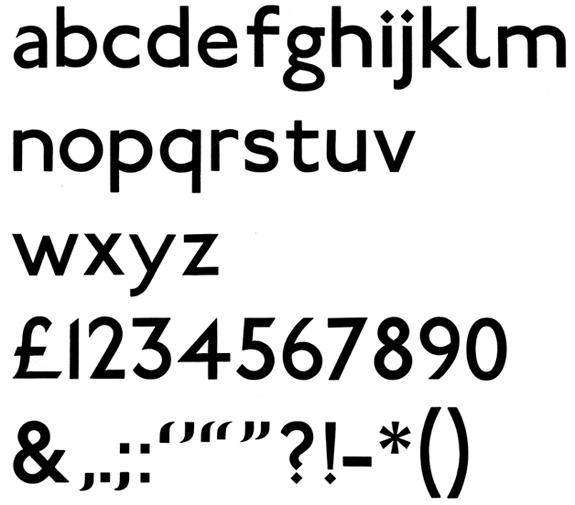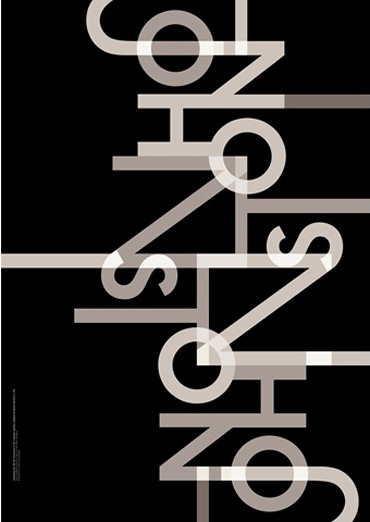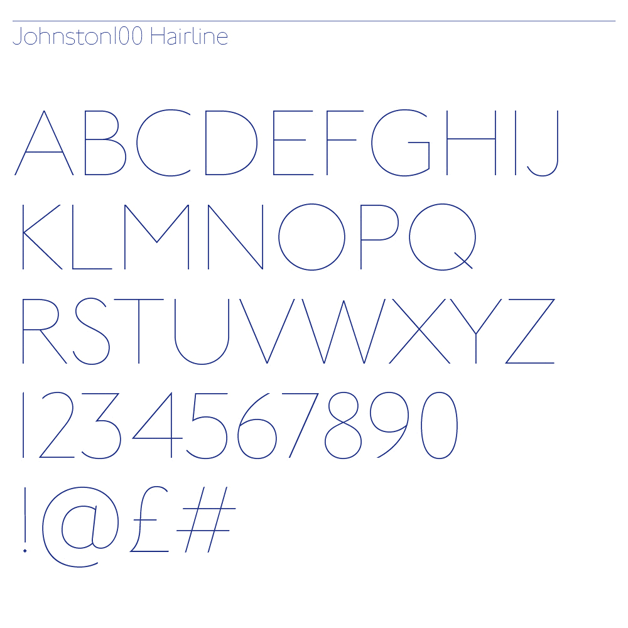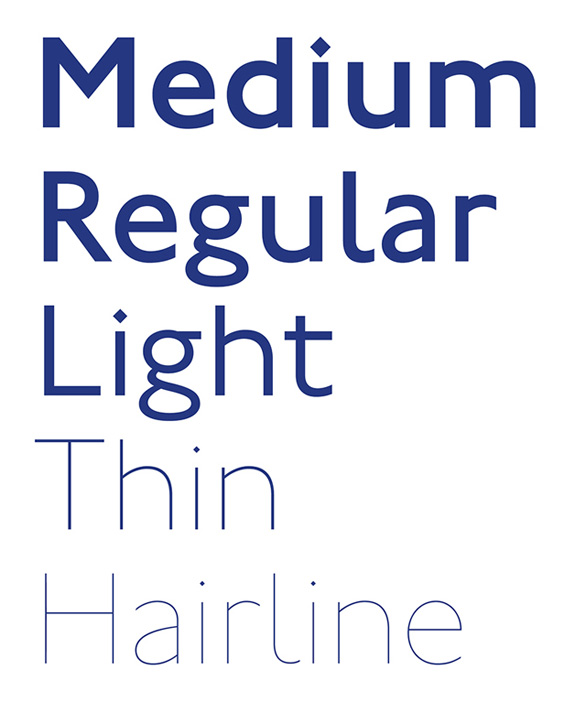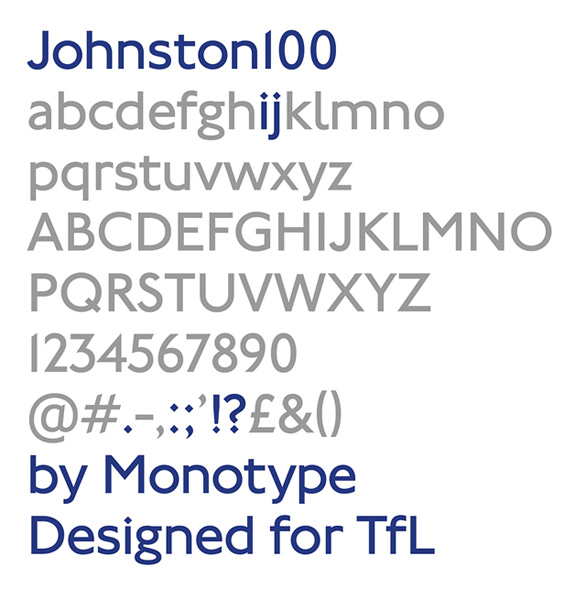
¿Cómo celebran los londinenses los 100 años de uso de la Johnston para todo el transporte de la ciudad de Londres? Con una familia tipográfica, por supuesto. Johnston100 tiene todas las cualidades del original, remasterizados para la era digital.
En 1916 Edward Johnston creó una original tipografía para el metro de Londres. Esta tipografía sans serif es un referente visual de Londres.
Imagen escaneada de la tipografía Johnston original, perteneciente al libro "La escritura de Londres", de Banks & Miles
Frank Pick, ex director gerente de transporte de Londres, jugó un papel decisivo en la definición de su identidad visual a principios del siglo XX. Encargó a Johnston diseñar una familia tipográfica original en 1913, trabajo que se completó en 1916. Los diseños originales de Johnston sirvieron como base para Johnston100.
Monotype tuvo el honor de crear Johnston100 para marcar 100 años de la tipografía, y además de implementarla en todo el sistema de transporte de Londres.
La compañía Pentagram, SEA y Alan Kitching (entre otros) diseñaron algunos de los posters de edición limitada que se venden en el Museo de Transporte de Londres.
El espíritu de la original
Durante las fases de investigación y diseño, la directora de Monotype Nadine Chahine y diseñador Malou Verlomme investigaron la tipografía original, incluso hicieron una visita al depósito del Museo del transporte de Londres para consultar los materiales base.
El proceso de diseño duró 3 meses, de enero a marzo de 2016. Verlomme dijo: “Nuestro principal objetivo era volver al espíritu del diseño original. Nos enfocamos más en los dibujos originales, los tipos de madera y carteles, más que otras versiones digitales”. “Johnston100 es otro capítulo en el legado de Johnston, un nuevo paso en esta tipografía en constante evolución“.
Chahine (izquierda) y Verlomme (derecha) visitaron el depósito del Museo del transporte de Londres para investigar el trabajo original de Johnston.
Johnston100 tiene cinco pesos incluyendo dos nuevos pesos, hairline y thin. También incluye la revisión de algunas de sus caracteres emblemáticos, como la g. La Johnston100 puede ser utilizada en una amplia variedad de idiomas.
Johnston100 es fiel a los diseños originales de Edward Johnston, que es importante teniendo en cuenta cómo la tipografía ha evolucionado a lo largo de los años. Verlomme hizo hincapié en cómo Johnston “ha pasado por muchas iteraciones y transferencias tecnológicas” y ve que Johnston100 "mantiene la tipografía viva, y en sintonía con los usos actuales.”
El legado sigue vivo
Chahine dice que Johnston100 es una actualización, ya que se mantiene fiel al material original. “La tipografía había perdido algunas de sus características originales y tratamos de rescatarlas nuevamente.” “Al igual que la original, Johnston100 tiene tildes de diamantes (a veces llamados puntos) en la parte superior de la i . Aunque la Johnston utilizaba cuadrados en los signos de puntuación 'j.' (;:.?!), Johnston100 utiliza la forma de diamante para lograr una apariencia más unificada".
Al igual que la Johnston original, Johnston100 no tiene un variable itálica. Pero tiene diferentes proporciones en comparación con su homónima y es más ancha para dar un “sensación visual más relajada” de acuerdo a Verlomme. Johnston100 está destinada para impresión, digital, móvil, texto en pantalla, etc.
Una tipografía de ayer, de hoy y mañana
Chahine encuentra la obra original de Johnston tan relevante hoy como lo fue hace 100 años.
“Johnston es un diseño atemporal, de lo contrario no habría sobrevivido durante 100 años. El trabajo que hicimos ha ayudado a dar consistencia a la familia de pesos en uso, y los pesos ligeros adicionales ayudan a darle una voz tipográfica más matizada que pertenece a este siglo y sus tendencias de diseño. El diseño de alta calidad y la mirada atenta de la empresa de Transporte de Londres se asegurará de que esta tipografía siga viva para muchas más décadas.”
Johnston100 comenzará a aparecer a finales de este año (2016) y se utilizará en la nueva línea de tren que está programada para abrir en 2018. Más información sobre Johnston100 en la web de Monotype y en Vimeo.